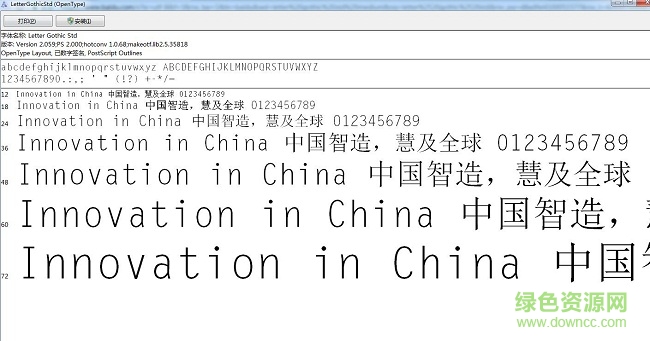
lettergothicstd字體包收錄了lettergothicstd bold、regular、medium以及l(fā)ettergothicstd-boldslanted等不同大小的英文字體,常規(guī)、粗體、細(xì)體都有,筆畫生動,用處多多,歡迎需要的朋友免費(fèi)下載使用!